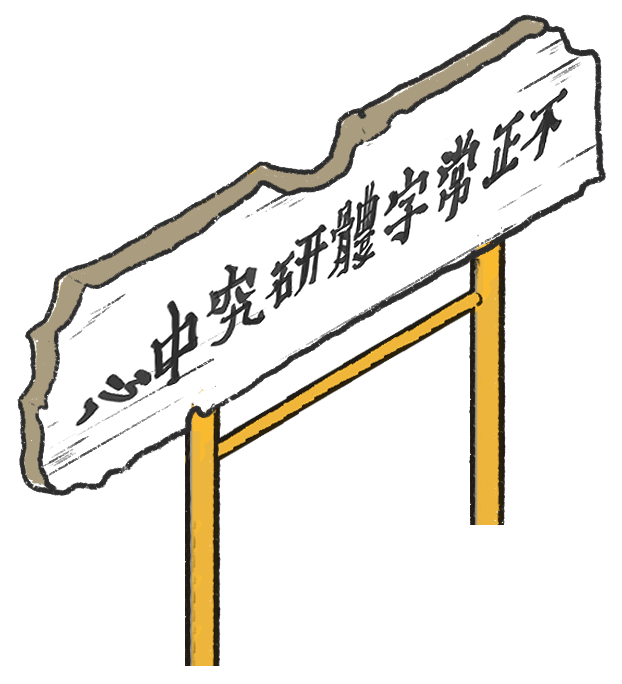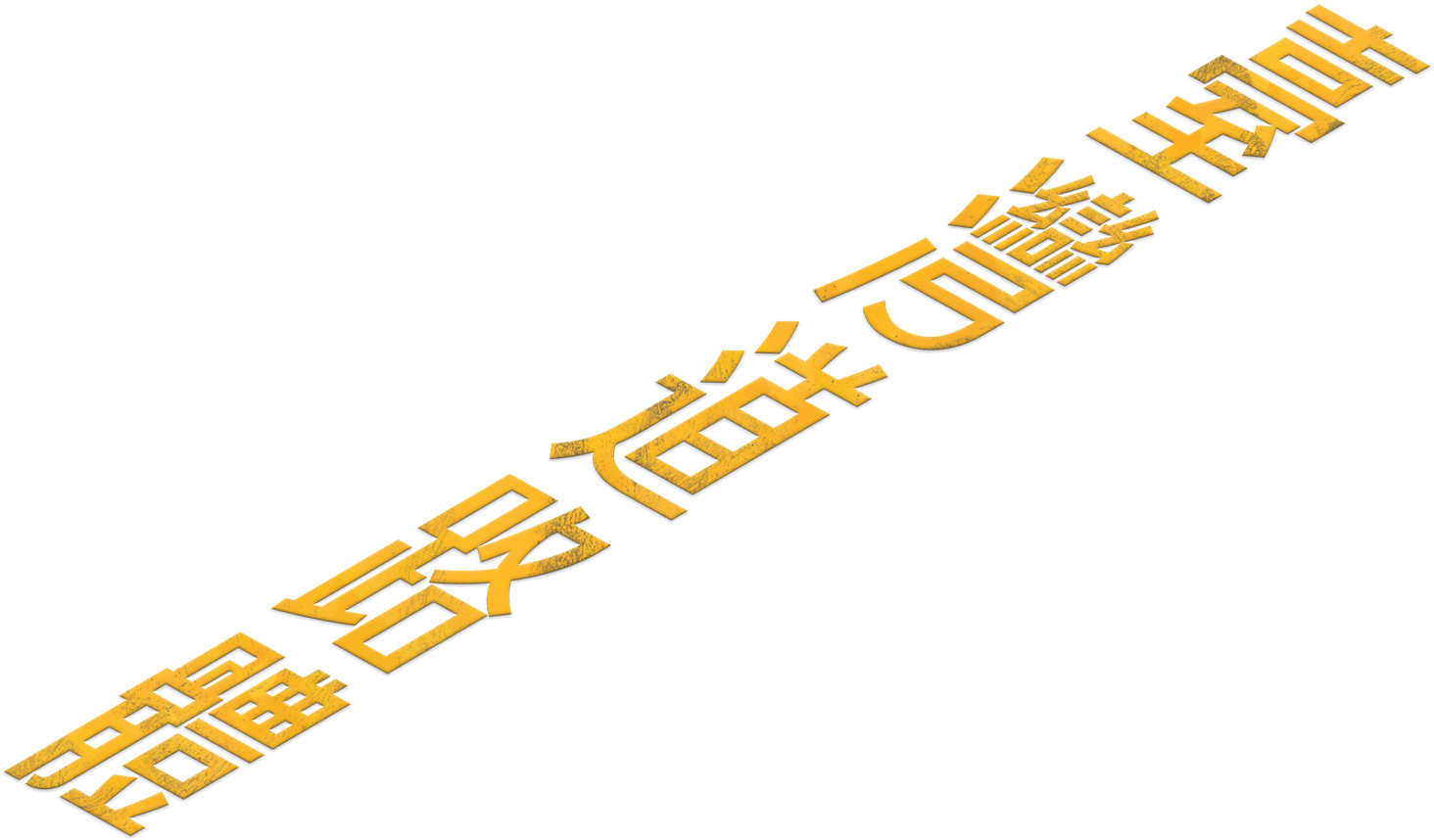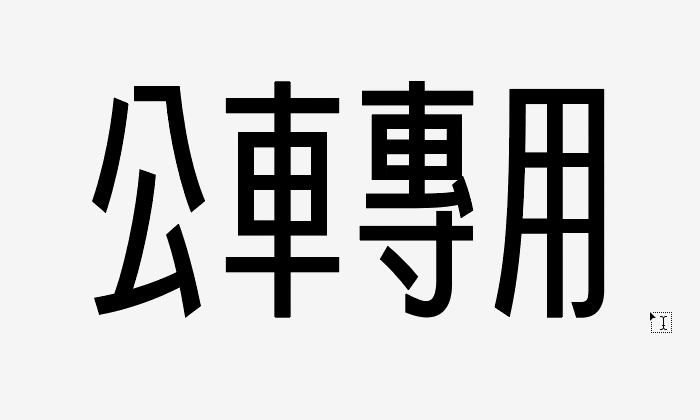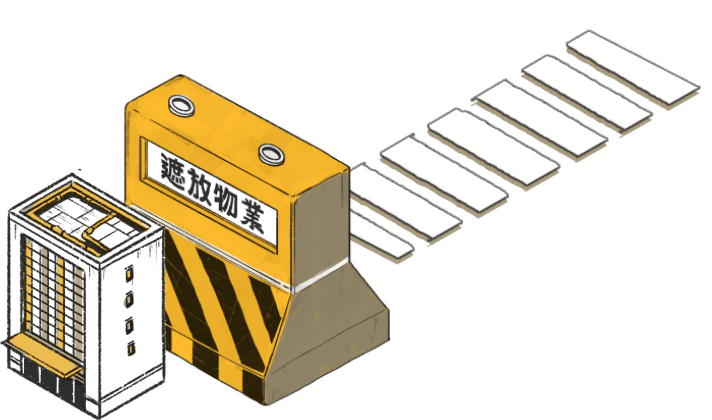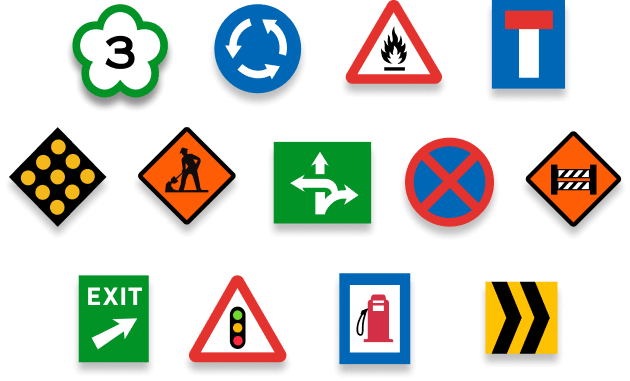
#變窄了,路線更寬廣
臺灣道路體
大家的版面收納大師
窄字體節省空間,更創造風格
啟發自道路標線的字體...
源自普通上班族湯六每天通勤生活中的觀察 : 以 6 年時間落實為完整字體設計。天然窄體,能放進更多資訊。深植人心的行動力,更特別適合 交通、動力、運輸、能源相關主題。
深植人心的行動力,更特別適合交通、動力、運輸、能源、電子商務等相關主題。
排版時,可別為了塞資訊
而委屈了大家的眼睛
同樣版面放了臺灣道路體,
立刻收納得整整齊齊
內含原汁原味道路風味(!?
以字型內建替換字符,
讓你自由選用台灣道路上常見的真實寫法,
還原道路標線字體的風味!
除了文字,
更有交通圖標小彩蛋藏在裡面
在地的字體,
其中內涵也很在地
臺灣道路體,當然要製作臺灣專用的文字!
不只有漢字、歐文、數字、香港常用字,
更包含台語、客語常用漢字以及台語、客語、族語羅馬字喔!
變窄不變形,一用就有型
十八般武藝,什麼都會!最接地氣的字體,
準備在你的作品上大展身手
自由品味,道路的文字風味
空間不夠用,字又要很大,只好全部暴力壓窄╮(╯_╰)╭